Mətni seçib Fonts.. dialoq qutusunda Advanced tab bölümündə OpenType Features zövqümüzə uyğun dəyişiklikləri edə bilərik. Fərqi göstərmək üçün aşağıda misal var:
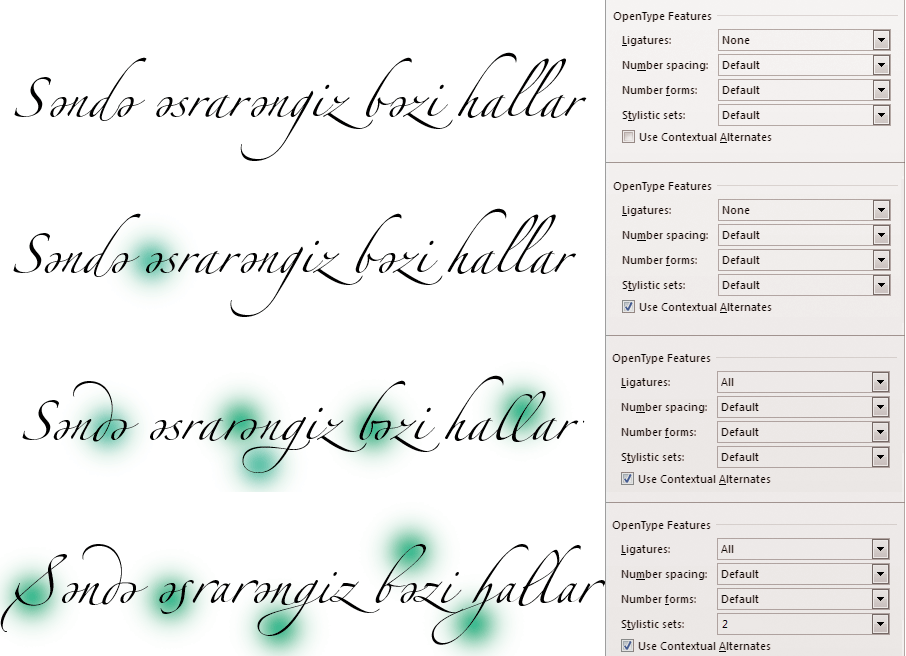
Mətni seçib Fonts.. dialoq qutusunda Advanced tab bölümündə OpenType Features zövqümüzə uyğun dəyişiklikləri edə bilərik. Fərqi göstərmək üçün aşağıda misal var:
Mətni seçib Character pəncərəsində zövqümüzə uyğun dəyişiklikləri edə bilərik. Fərqi göstərmək üçün aşağıda misal var:
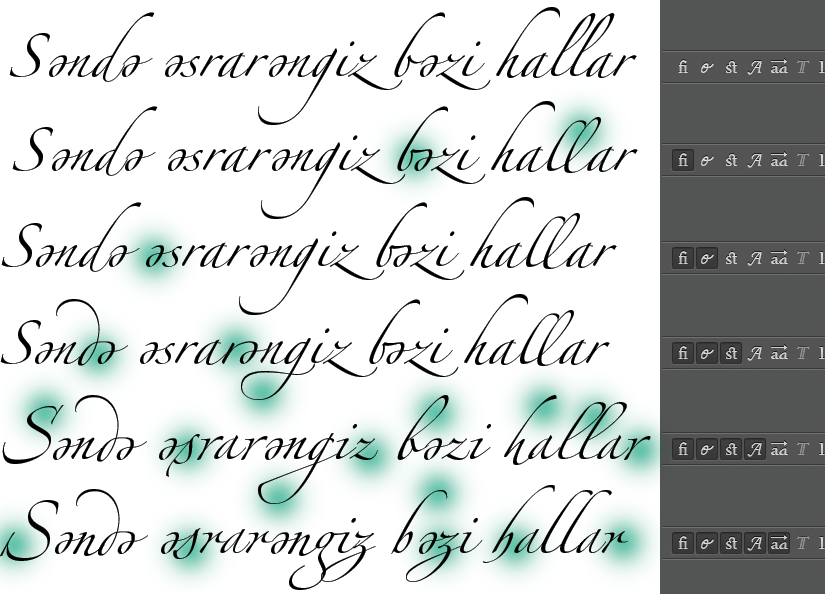
Aşağıdakı şəkildə liqatura növləri izah göstərlib: